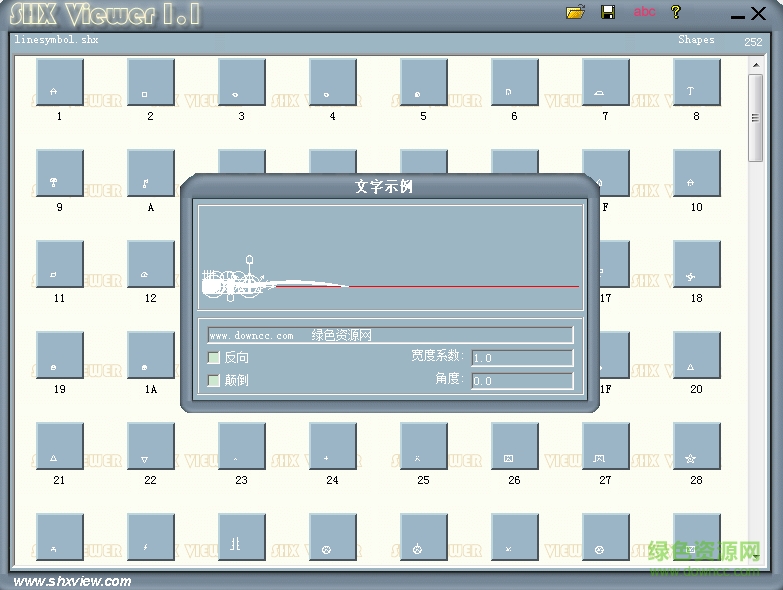
linesymbol.shx是一款非常有特色的cad字體,這款字體可以打出各種特色的符號(hào),很多cad圖紙都使用了這款字體,需要的朋友歡迎來綠色資源網(wǎng)免費(fèi)下載使用。
shx字體文件,是一種用矢量描述的形文件,shx專門的中文字庫,這種字庫的文件擴(kuò)展名為.SHX,autocad中用戶可自己定義擴(kuò)展名為 “ .shp”形定義字體文件。